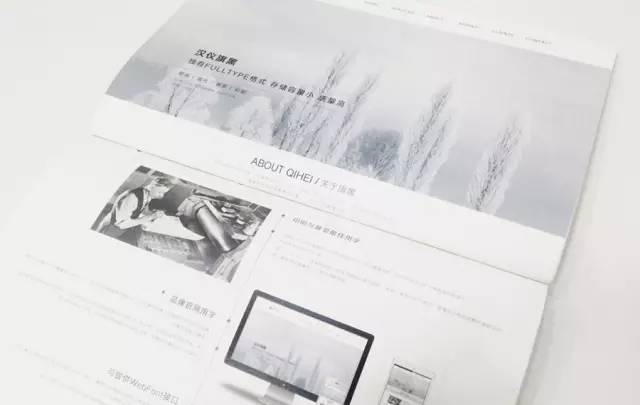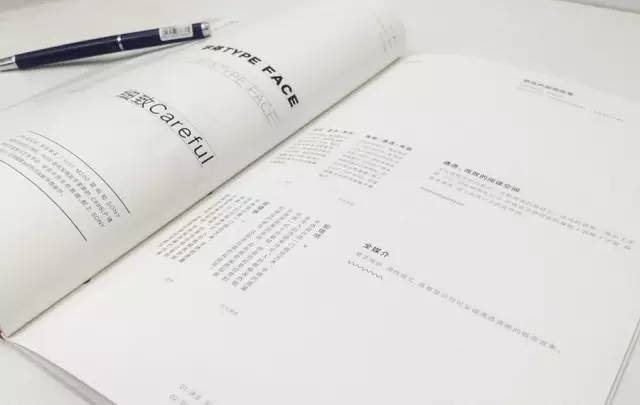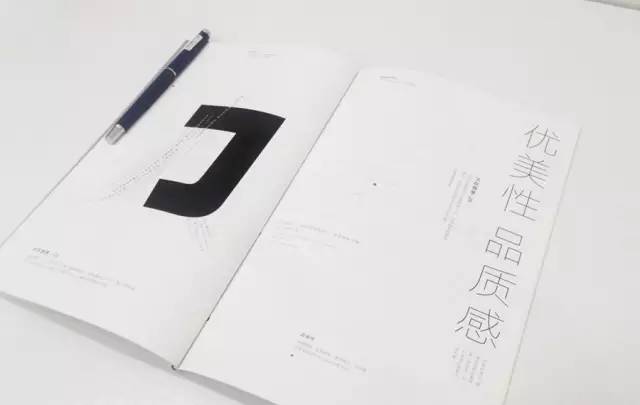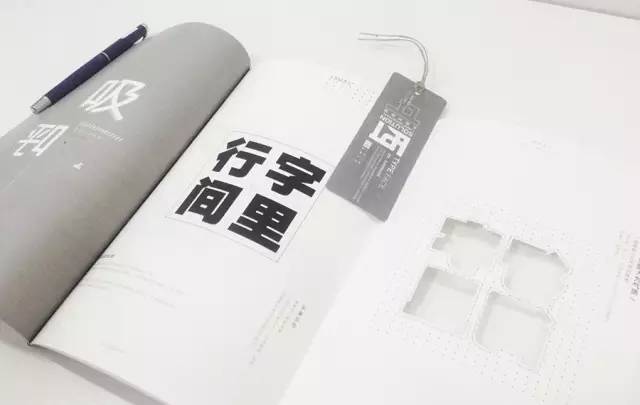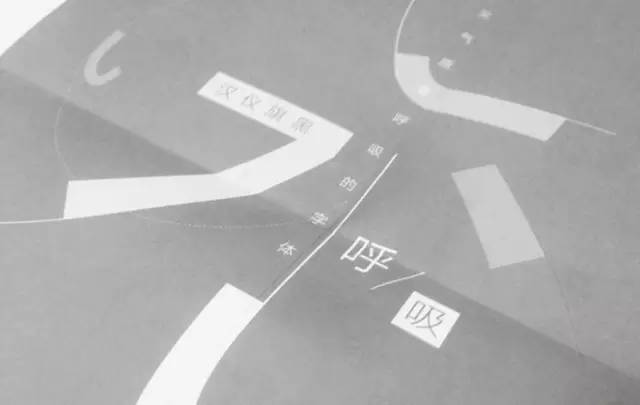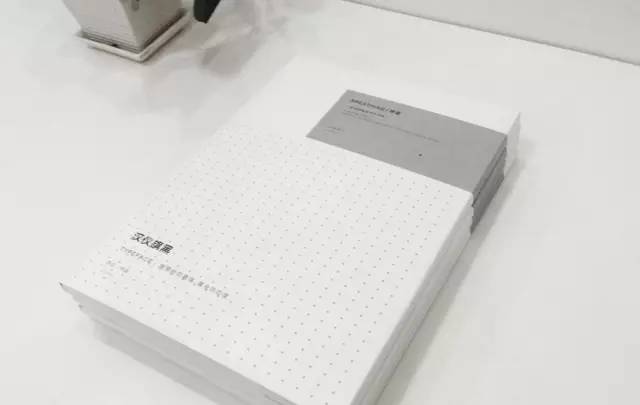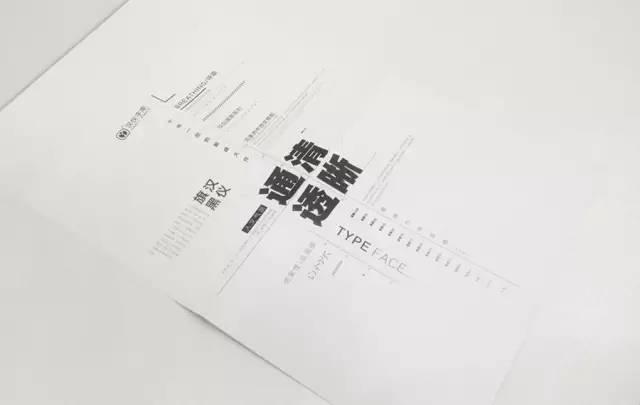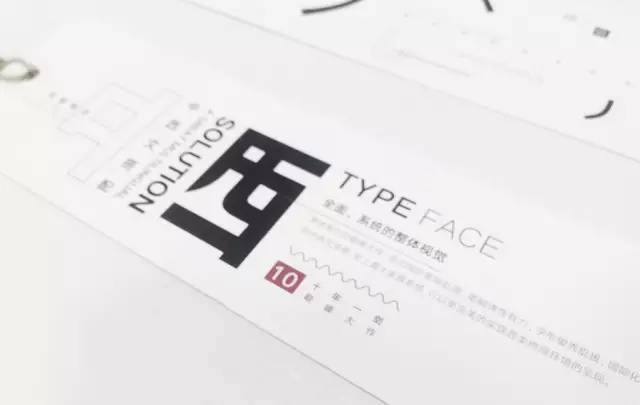
汉仪旗黑字体介绍,汉仪旗黑使用案例、适用场景
品牌标志配字,即标准字
标准字是专为品牌选择或设计的字,标准字是专门搭配logo使用的,里面包括企业的中文全称、简称和英文全称、简称。
这部分的字是要连同标志一起注册的,若是使用字库里的个别字体,也是需要得到字库公司授权,没经过字体公司授权使用都属于侵权行为;第二种情况就是找专门的设计师或设计团队设计的字,这种字体是具有独特性、唯一性和专属性,一旦注册下来,这几个字形版权就属于该品牌,任何人及组织使用时需经过该品牌的同意。这些标准字是品牌最基础,也是品牌基因中最重要的部分。
品牌基因
品牌logo图形、品牌标准字、品牌色彩、品牌辅助图形、品牌文化等,这些最基础元素,组成了品牌对外的形象。在传播的过程中,才能呈现出统一的形象。而在这些元素里面,品牌的logo图形和标准字是最重要、最核心的部分。
下面我们来看看旗黑在这方面的表现:
以上使用了汉仪旗黑的中文及英文,在做品牌标准字时,与logo图形(虚拟的图形)的搭配接近完美。
旗黑在做标准字时,无论对应什么样的品牌,15种字重可以任意选择,这样可以满足与LOGO图形的任意搭配。
品牌专用办公字体及印刷字体
办公字体OR印刷字体?
品牌专用字体是指品牌为了塑造对内、对外良好及统一的品牌形象,根据品牌的性质选择的一系列字体,这个在设计VIS(品牌视觉识别手册)里面就有体现,也是其中的一部分。
品牌专用办公字体
是指品牌在企业内部,同事之间、部门之间等使用的字体,比如企业内部文件,信件,名片、信封、信纸等。
品牌专用印刷字体
一般是指品牌对外宣传物料用字,比如企业画册、宣传页、易拉宝等,它和办公字体也没有严格的界限,但都需要根据品牌的性质来选择。
旗黑在专用字体领域很有潜力
1.旗黑拥有15种字重,可以满足品牌任何方面的用字,比如:标题的选择范围非常自由,适合内文排版的40--65号字重区间内包含6个细分跨度,可以满足更细腻的排版需求,而25、35号字重可使用在备注或其他说明性文字,比如地址或者一些修饰性文字。
2.旗黑在排版上,无论是长篇幅的横向排版,特性的竖排版,亦或是特点环境下的锯齿状缀文排版,汉仪旗黑都表现出绝佳的视觉效果。
下面看看旗黑的表现:
以上图例中可以看出,汉仪旗黑在品牌专用字方面具有独特而系统化的优势,而且在平面排版中的表现更加出彩,无论是横向排版,还是竖排版,亦或是装饰性的特殊排版样式,汉仪旗黑都可以呈现出优质的视觉效果。
品牌宣传物料用字
品牌宣传物料主要指企业的宣传手册、单页、海报等,这方面的用字是根据品牌专用字延展来的,主要的就是文字的大小、粗细的把握。
宣传物料用字主要考验字体排版
这里要说的是旗黑在排版方面的优势,在画册等宣传物料中主要就是标题及内文的排版、中西文的搭配,对字体的要求很高,字体整体重心的统一、结构的把握、字面的控制等。
从文字的结构来看,汉仪旗黑的结构更加严谨,部件也更加规范。字面上讲,共性强的字,字面大、笔划部件撑得满,排版效果好,但字形易呆,不易写漂亮;个性强的字通常字面较小、排版效果稍差,但字形易漂亮。汉仪旗黑在设计时,在字的共性和个性这对矛盾中寻找平衡点,同时,对部件的大小、笔划斜度、高低位置等进行了多次实验。实验结果,旗黑字体结构更严谨,字面大而不过,字形整齐、秀丽、亲切、怡人眼目。
在排版中不难看出,汉仪旗黑的整体感觉,更加的精致、简洁,因为旗黑拥有15种字重的优势,在标题、副标题、内文大小、节奏把握都有出色的表现。加上中西文能够完美的搭配,这样一款字体就可以解决所有排版的问题。
汉仪旗黑-105,是大型海报大标题最佳用字
无装饰线风格的字体风格,字的重心略微偏高,字形方中显长,字面设定的大而不过,让撇捺有舒展的空间。具有庄重、典雅、简约、使用面广等特性。
品牌官网用字
网页是品牌对外传播重要的途径之一,网页的形象直接关系到人们对品牌的印象,官网用字的选择对品牌形象也是相当重要。
网页要适用于各种终端,但并不是所有品牌都会选择系统默认的字体而会更倾向于使用品牌定制的特有字体,这个时候我们要如何做呢?
不常用的字体就要采用图片的格式、嵌入式字体,但这些都有弊端:图片的格式文字用户不能复制,搜索网络关键词时搜不到;英文的嵌入式字体体积较小,加载速度快,用户的接受度相对较高;但对于体积庞大的中文字库,对网络环境的要求很高,将一整套的字体嵌入网站是不明智的。
可以嵌入仅在网页上使用的部分文字,那么一整套的字体如何提取出来这部分的文字呢?
那旗黑在网页或者移动端上面的表现如何?
网页用字其实和画册用字如出一辙,主要是排版的表现,而且还有屏显的效果,排版的表现在品牌专用字里面已经说明,在这里就说说屏显的效果。
汉仪旗黑是为印刷和屏幕显示通用字体而设计,所以着重考虑了如何在保持印刷字体美观的前提下,把曲线变为直线的问题,如:刂、扌、犭、阝等钩的处理,除使字体设计更为简约、爽朗,富有时代气息外,更增加了视觉的整齐度和设计感,使字体在屏幕显示上更为清晰易读。
汉仪旗黑的产品的设计理念,正是为了顺应时代的发展,在各种智能终端不断发展,界面信息交互性加强的情况下,通过字面、结构、内白以及间距方面的精细化设计,加上手写笔形的设计以及15个字号,长、方、扁三种类型的家族字体的打造,为多元化的设计作品提供更加具有人文气息的高质量作品。
产品格式、家族庞大
旗黑的产品格式是我比较喜欢的,软件里面仅一种命名,15种字重任意选择,除去了复杂的操作,很好的体验。
汉仪旗黑在字体字重的设计以及命名上也更加国际化、一体化。区别于传统的独立字重命名规则。汉仪旗黑采用数字的方式对字重进行分类、标识。在大系列家族化的产品设计中,可以让设计师更加直观方便的找到并使用。
旗黑精装版效果图